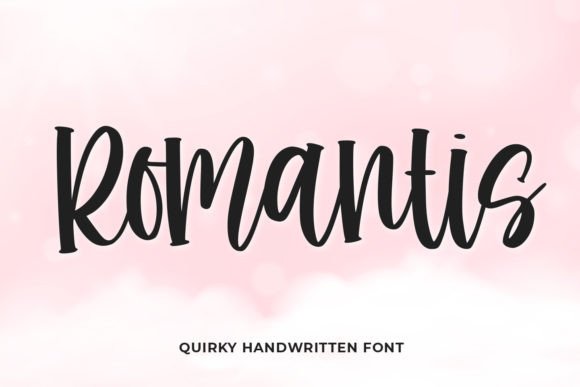
Romantis
Si vous recherchez des ressources de haute qualité comme Romantis, ce pack premium est un choix fantastique pour vos projets créatifs.
Que vous créiez des produits POD (impression à la demande), des invitations de mariage ou des visuels pour les réseaux sociaux, Romantis est un choix idéal.